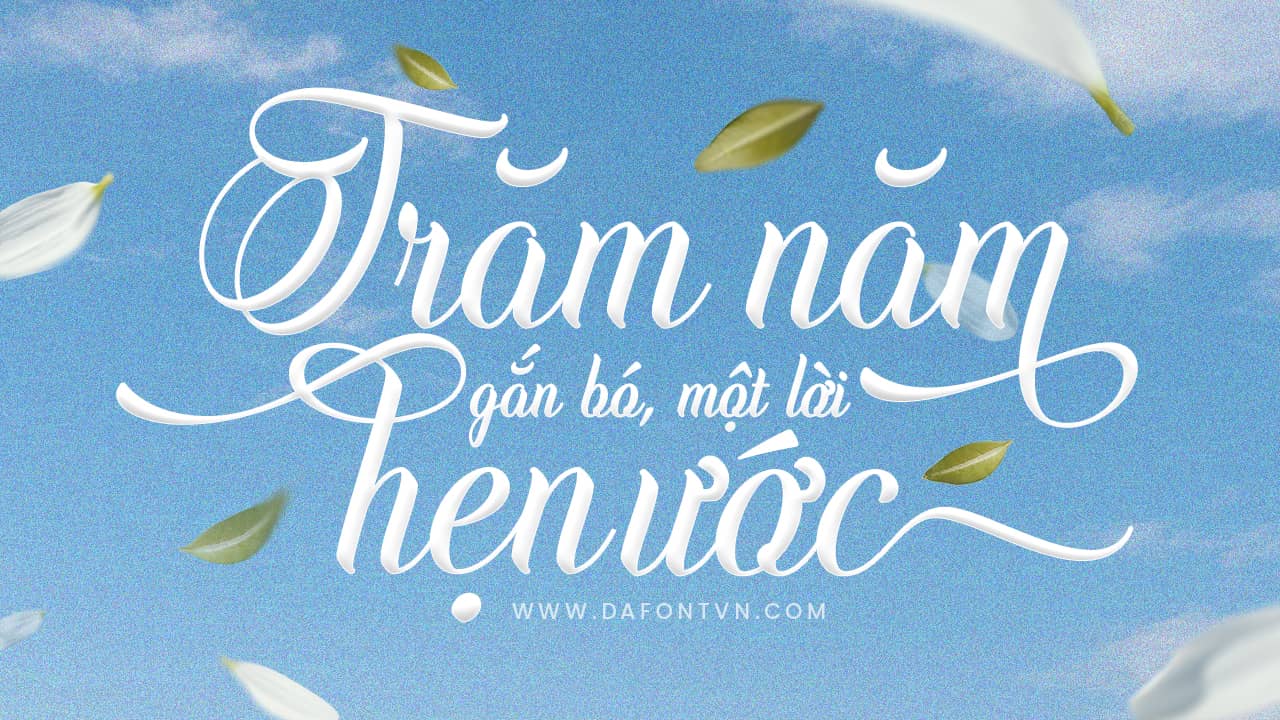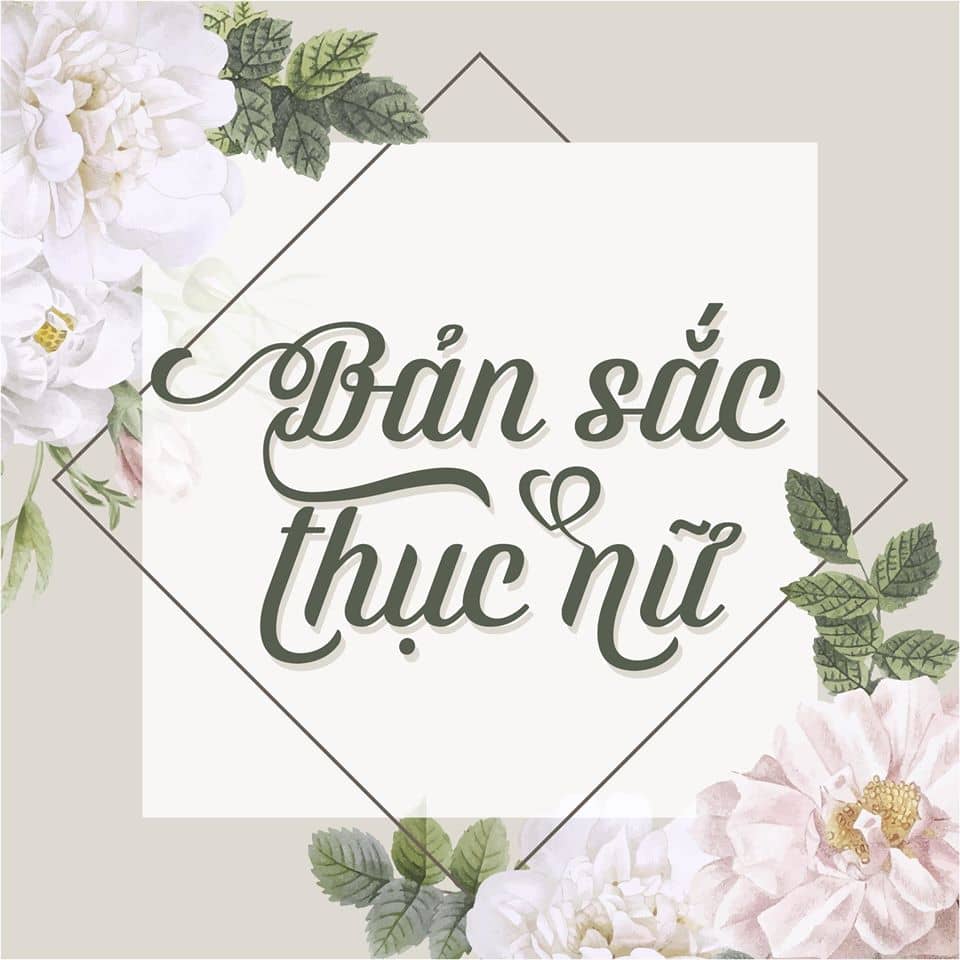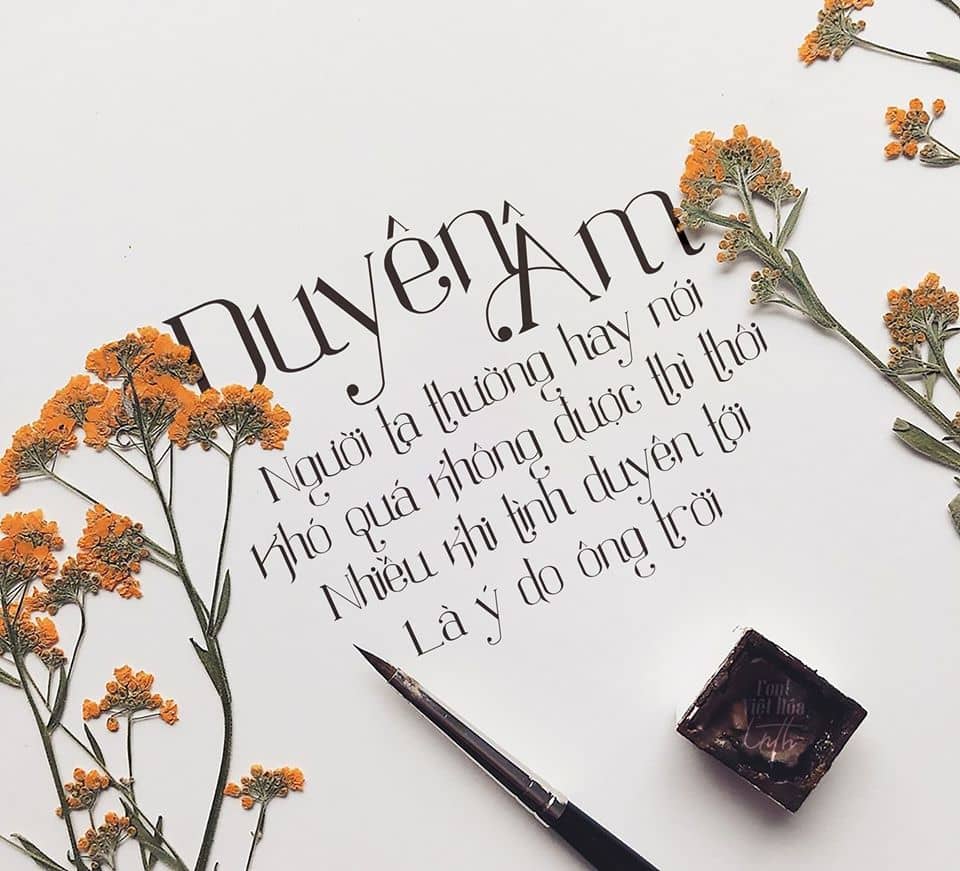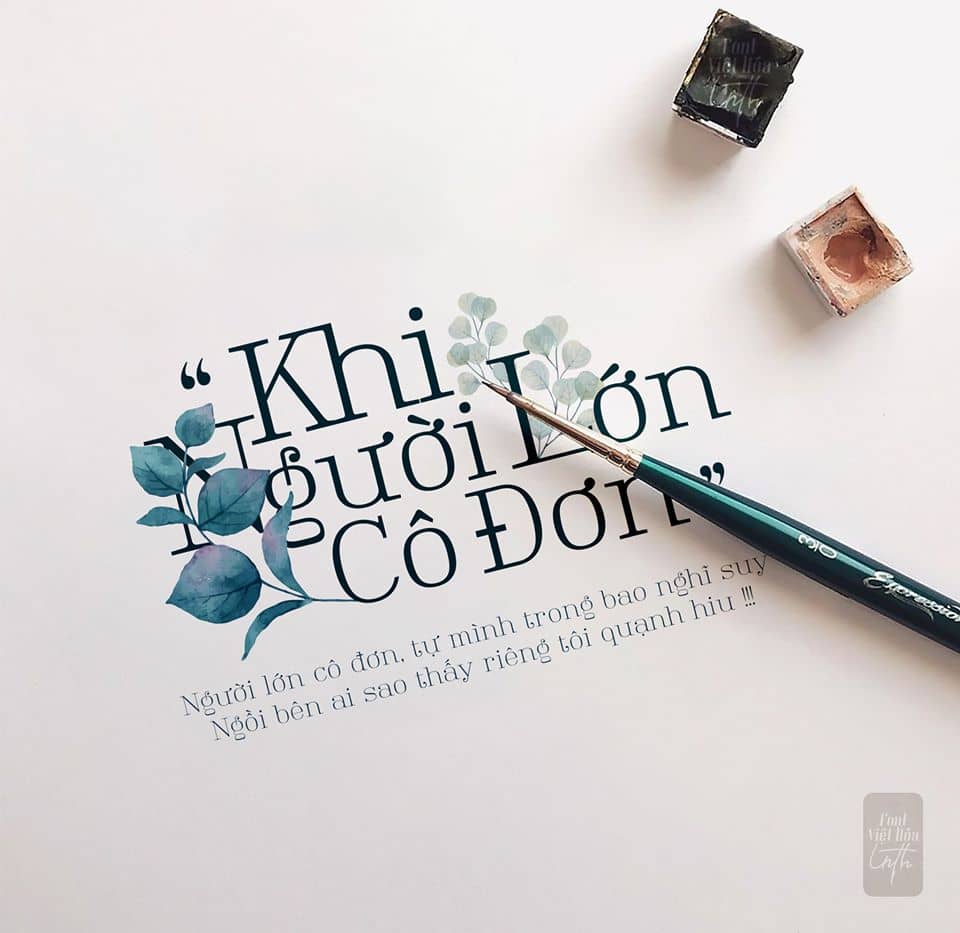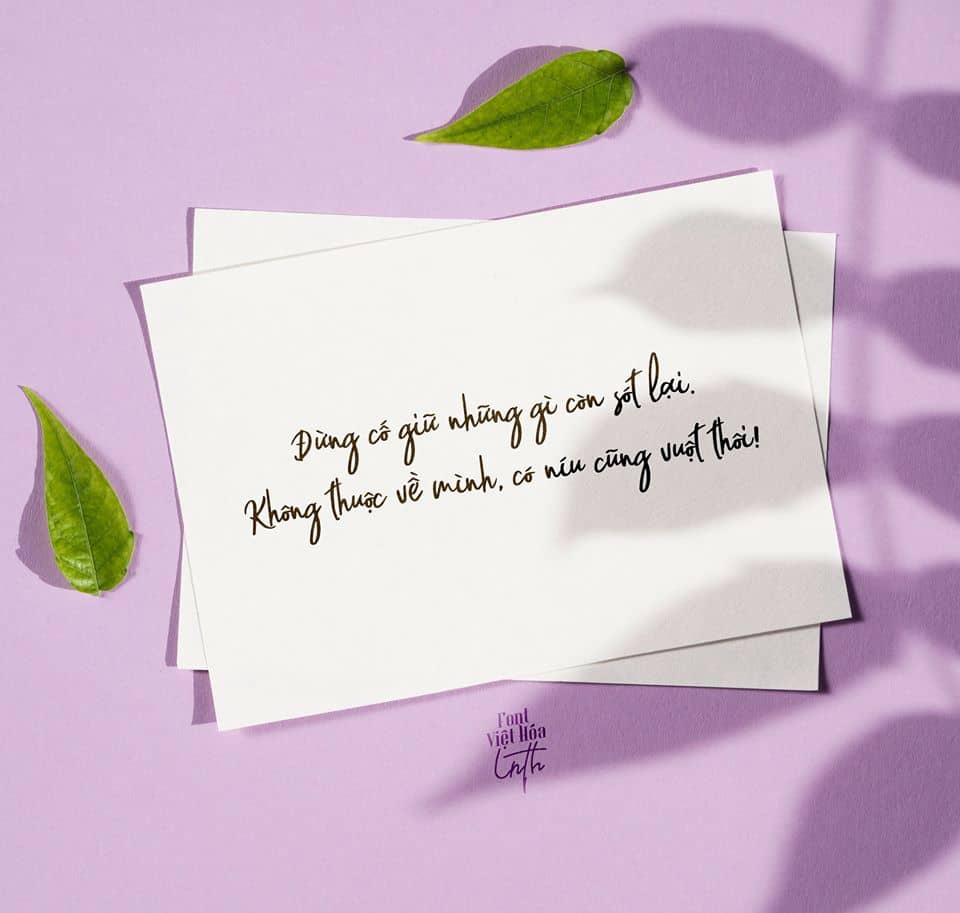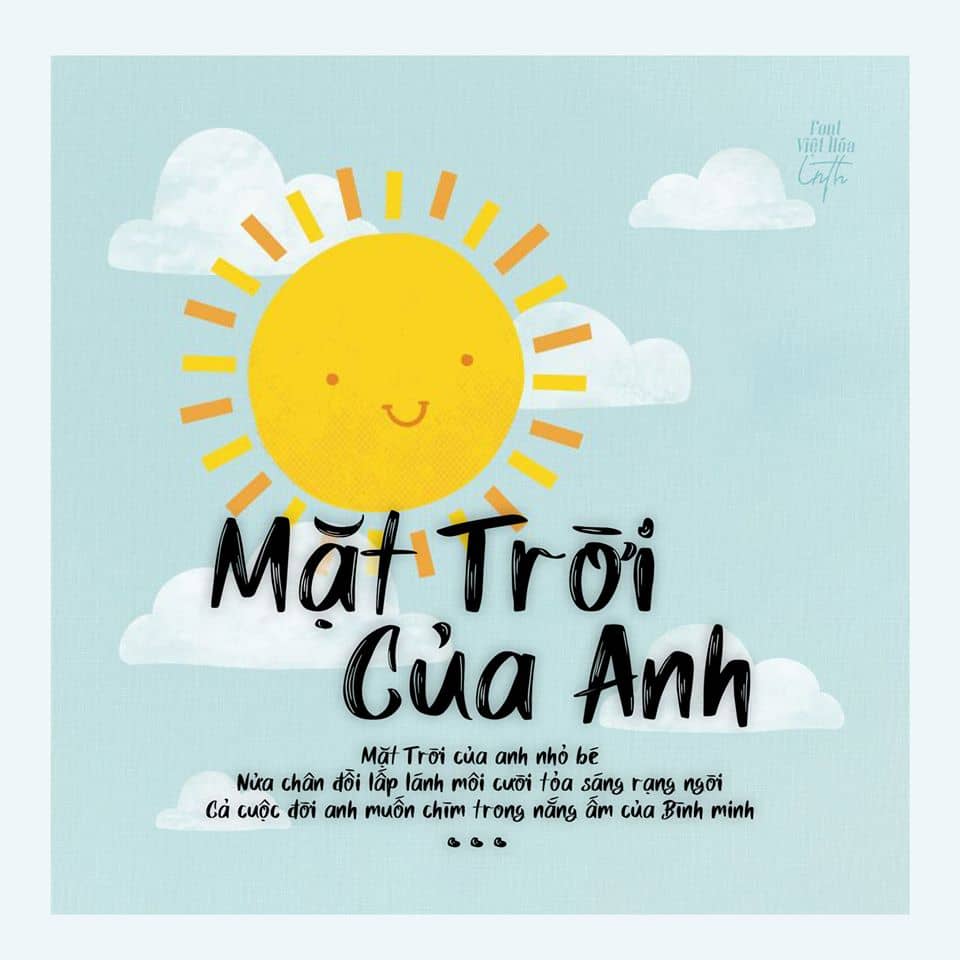
Tải 39 Font Việt Hóa LNTH Miễn Phi Tuyệt Đẹp Cho Designer
Giới Thiệu
Font chữ đóng vai trò quan trọng trong thiết kế đồ họa, giúp truyền tải thông điệp một cách hiệu quả và thẩm mỹ. Với nhu cầu ngày càng cao của designer, D3design chia sẻ bộ sưu tập 39 font Việt hóa LNTH tuyệt đẹp, hỗ trợ tiếng Việt đầy đủ, phù hợp với nhiều dự án thiết kế chuyên nghiệp.
Vì Sao Nên Dùng Font Việt Hóa LNTH?
Hỗ trợ tiếng Việt hoàn chỉnh: Không bị lỗi dấu hay ký tự đặc biệt.
Đa dạng phong cách: Từ hiện đại, cổ điển đến nghệ thuật, viết tay.
Tạo điểm nhấn độc đáo: Làm nổi bật nội dung, tăng sự thu hút cho ấn phẩm.
39 Font Việt Hóa LNTH Tuyệt Đẹp Cho Designer
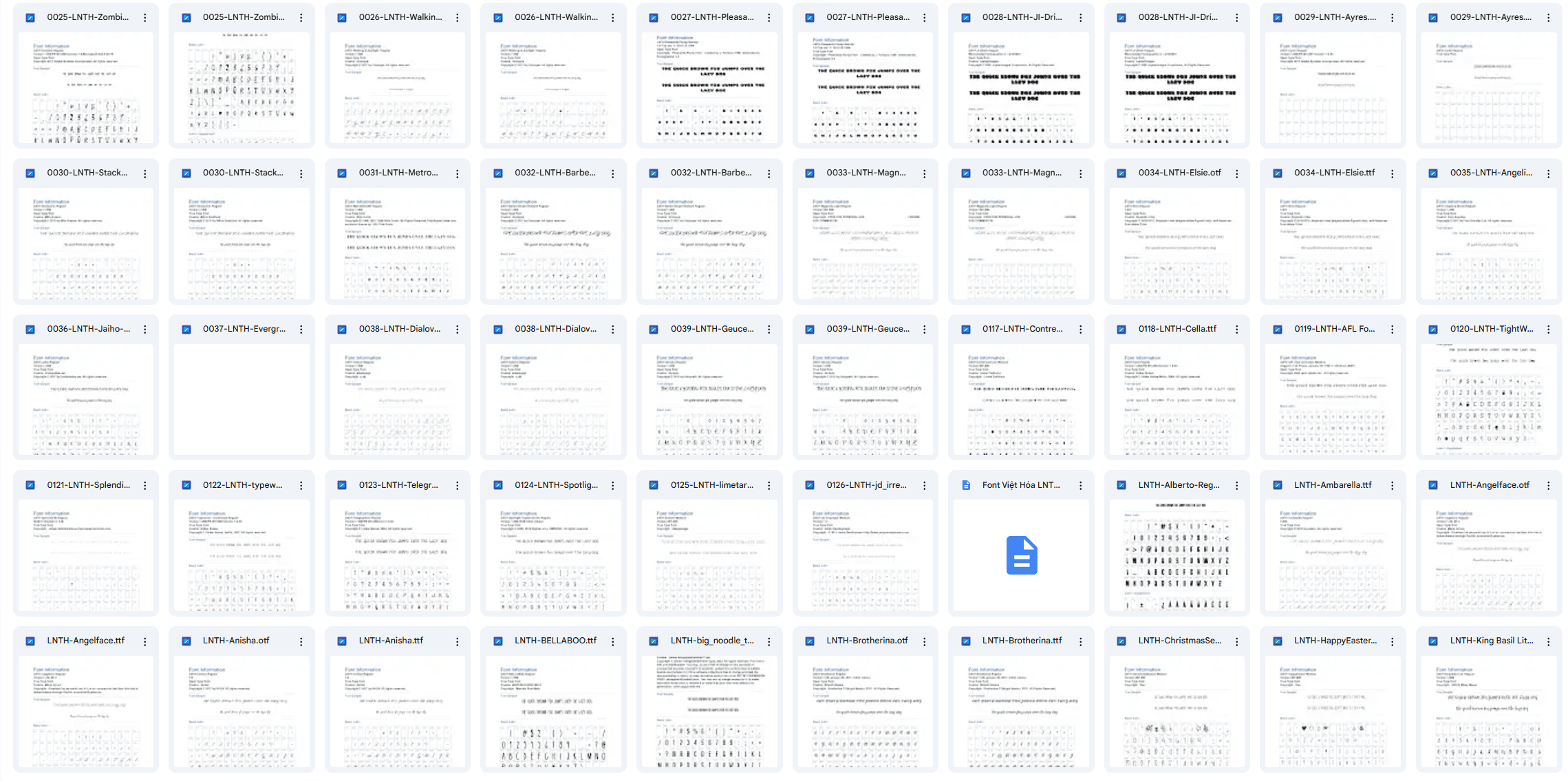
Mẹo Kết Hợp Font Chuyên Nghiệp
Kết hợp font Sans-serif và Serif để tạo sự cân bằng.
Sử dụng font Script cho tiêu đề, font đơn giản cho nội dung để tăng tính dễ đọc.
Tránh lạm dụng quá nhiều font trong một thiết kế để tránh rối mắt.